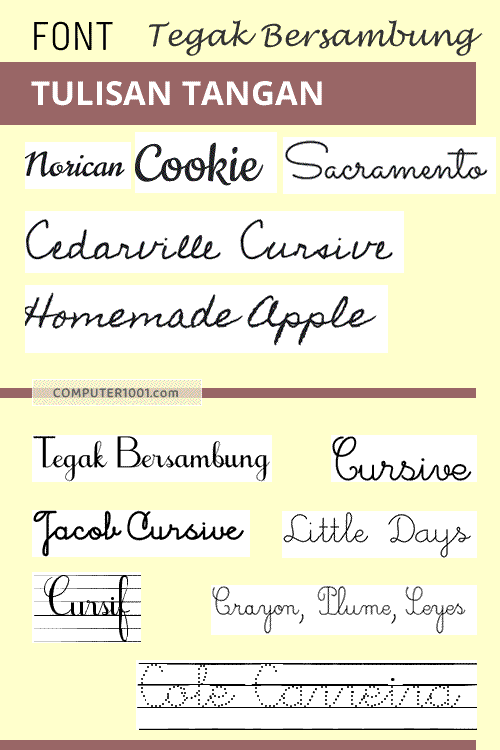
Handwritten atau handwriting font merupakan font yang bentuknya mirip tulisan tangan.
Tipe font ini bisa digunakan untuk membuat catatan aesthetic, caption video dan banner, brosur, poster quote, serta desain grafis lainnya.
Font Tulisan Tangan Keren
Artikel ini menyajikan koleksi font tulisan tangan yang ada di Fonts.Google.com dan Dafont.com.
Boleh dikatakan koleksi font tulisan tangan di situs ini semuanya bagus-bagus dan keren.
Bentuknya yang seperti tulisan tangan sendiri atau tulisan tangan biasa sangat cocok untuk menulis rangkuman pelajaran di catatan aesthetic.
Dan juga untuk konten lirik lagu, puisi, atau tutorial.
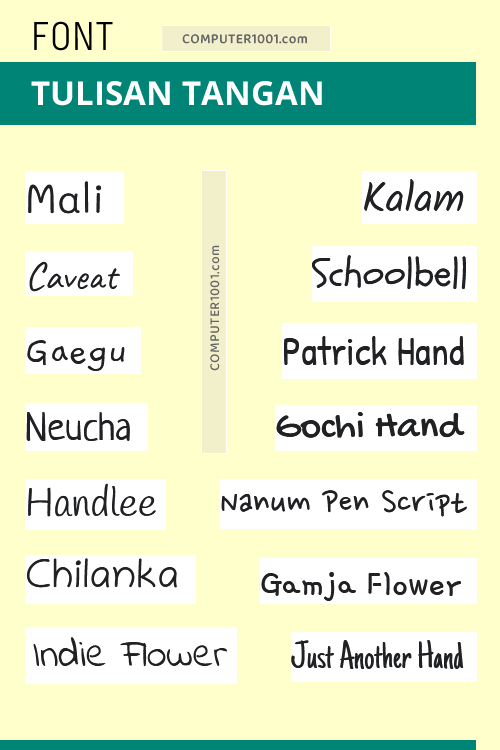
- Mali
- Kalam
- Caveat
- Schoolbell
- Gaegu
- Patrick Hand
- Neucha
- Gochi Hand
- Handlee
- Nanum Pen Script
- Chilanka
- Gamja Flower
- Indie Flower
- Just Another Hand
Sedangkan Dafont memiliki koleksi font tulisan tangan yang kreatif, unik, lucu, dan juga indah.
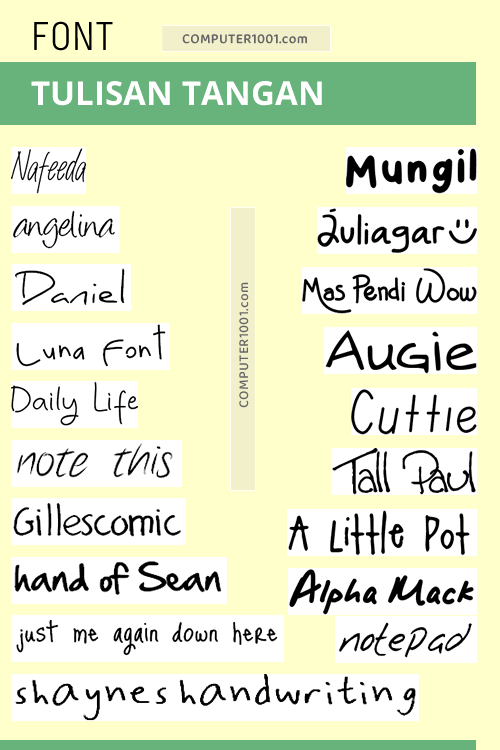
- Nafeeda
- Angelina
- Daniel
- Luna
- Daily Life
- Note this
- Gilles’ Comic Handwriting
- Hand of Sean
- Just me again down here
- Shaynes handwriting
- Mungil
- Juliagar
- Mas Pendi Wow
- Augie
- Cuttie
- Tall Paul
- A Little Pot
- Alpha Mack AOE
- Notepad
Font seperti Mungil dan Augie sangat bagus untuk caption gambar atau video.
Font Daily Life dan Cuttie memiliki bentuk yang imut.
Dan font Alpha Mack AOE memiliki koleksi huruf abc besar dan kecil. Lengkap dengan operator matematika, tanda baca, simbol mata uang, dan ada gambar hewan lucu.
Font Tulisan Tangan Jelek
Tulisan yang jelek sifatnya relatif.
Sebagian orang akan menganggapnya bagus, namun ada juga yang berpikir sebaliknya.
Khusus bagian ini, dipilih font yang tulisannya mirip cakar ayam, yang kelihatan sangat tidak rapi, tidak teratur, yang naik turun.
Atau kelihatan seperti baru belajar menulis atau ditulis pakai tangan kiri (bagi yang biasa menggunakan tangan kanan).
Font ini bisa digunakan untuk ilustrasi cerita anak-anak, kartu ucapan, atau tugas sekolah lainnya.
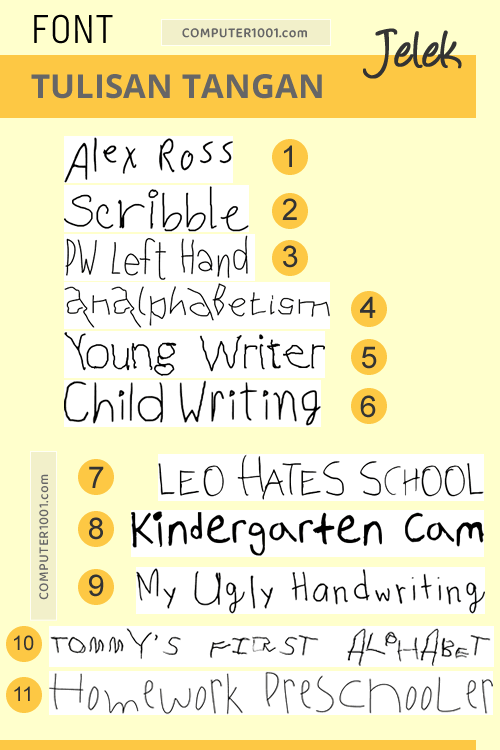
- Alex Ross
- Scribble
- PW Left Hand
- AnAlphaBetism
- Young Writer
- Child Writing
- Leo Hates School
- Kindergarten Cam
- My Ugly Handwriting
- Tommy’s first alphabet
- Homework Preschooler
Font Tommy’s first alphabet kelihatan persis tulisan tangan pensil jelek. Huruf p font ini benar-benar sangat berantakan, lebih mirip coretan huruf o atau kertas yang diremas jadi bola.
Beberapa font memiliki koleksi glif (glyph) yang lengkap. Contohnya, font Leo Hates School.
Walaupun namanya begitu, font ini memiliki huruf a-z kapital, angka 0 – 9, tanda baca, tanda kurung, operator matematika, huruf tanda aksen, dan simbol mata uang.
Dan bila kita mengetikkan simbol tilde (~) akan muncul noda goresan.
Sedangkan font Homework Preschooler, ukuran besar kecil huruf tidak sama.
Namun bila diperhatikan dengan seksama, font ini sesungguhnya cantik. Cocok juga dijadikan sebagai font display atau headline.
Font Tanda Tangan
Selain 3 Cara Mudah Membuat Tanda Tangan Digital Dokumen Word dan Excel ini, juga ada font yang didesain untuk tanda tangan.
Dapatkan font tanda tangan keren berikut di Dafont.
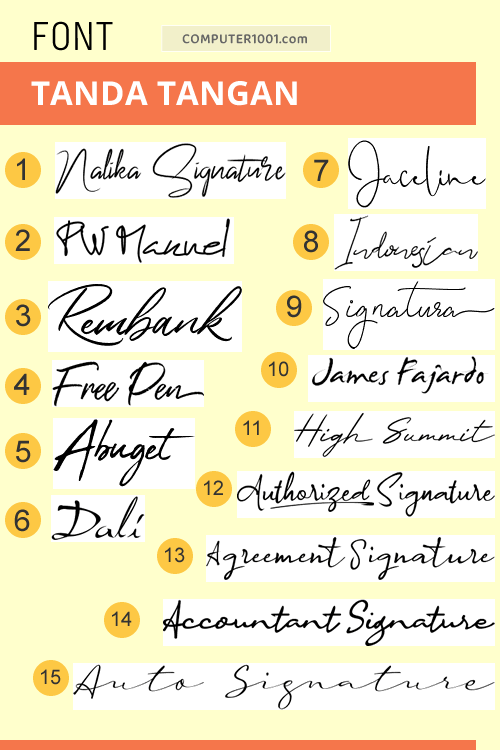
- Nalika Signature
- PW Manuel
- Rembank
- Free Pen
- Abuget
- Dali
- Jaceline
- Indonesian
- Signatura Monoline Script
- James Fajardo
- High Summit
- A Authorized Signature
- A Agreement Signature
- a Accountant Signature
- A Auto Signature
Font Tulisan Tangan Tegak Bersambung
Tulisan kursif (cursive) atau huruf tegak bersambung adalah gaya tulisan tangan yang huruf-hurufnya ditulis secara bersambung.
Di komputer kamu mungkin sudah ter-install font tulisan sambung, seperti Segoe Script, Lucida Handwriting, Edwardian Script, dan Kunstler Script.
Font Cole Carreira adalah font tegak bersambung putus-putus atau berupa titik-titik dan juga ada garisnya. Sehingga bisa digunakan oleh anak-anak yang sedang belajar menulis huruf dan angka.
Font Tegak Bersambung IWK memiliki bentuk mirip huruf tegak bersambung baku yang sesuai dengan EYD.
Bila ingin tulisan sambung yang miring, coba beri gaya Italic pada tulisan tersebut dan lihat hasilnya apakah sesuai seperti yang diinginkan.